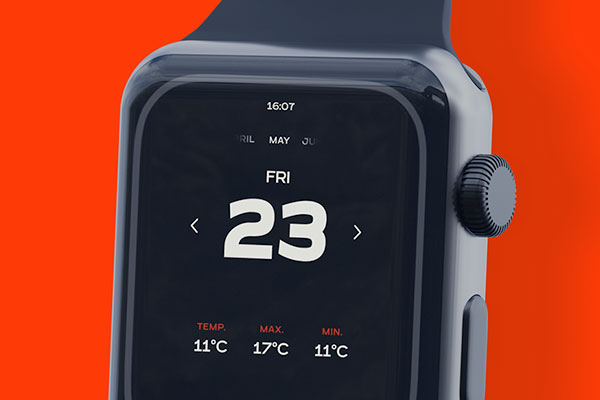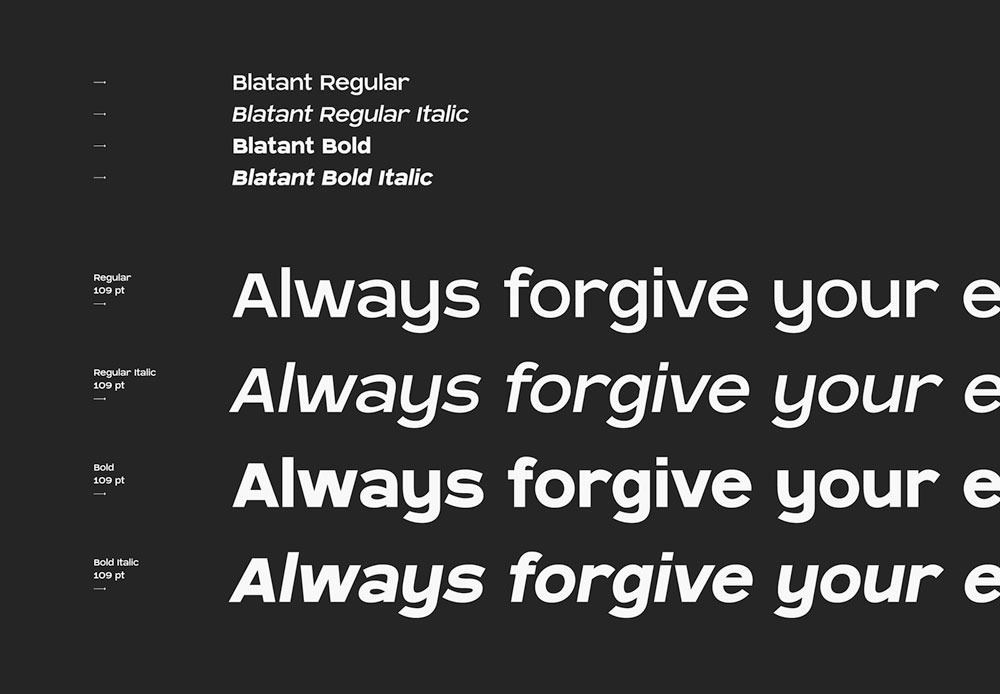
Blatant字体
Blatant是由阿根廷设计师Tomás Castiglioni创作的一款出色的英文字体。这款字体的通用性较强,笔画较粗,给人一种稳重的感觉,旨在引起人们的注意。无论是在海报设计、品牌标识、网站制作还是印刷品中,Blatant都能够成为视觉作品的焦点,不会被忽视。
Blatant字体包含4种不同粗细和斜体,自由字体已在下方提供预览图,您可以根据需要进行选择。字体作者在Behance平台上发布了Blatant字体,并声明个人及商用是完全免费的。这为您的设计提供了更多的自由度和灵活性,让您能够轻松地将这款字体融入到各种项目中去。
Blatant字体的区别在于其广泛的替代性高框标牌集,让您的设计作品更加独特。现在就来免费下载Blatant字体,让您的设计焕发出独特的魅力吧!